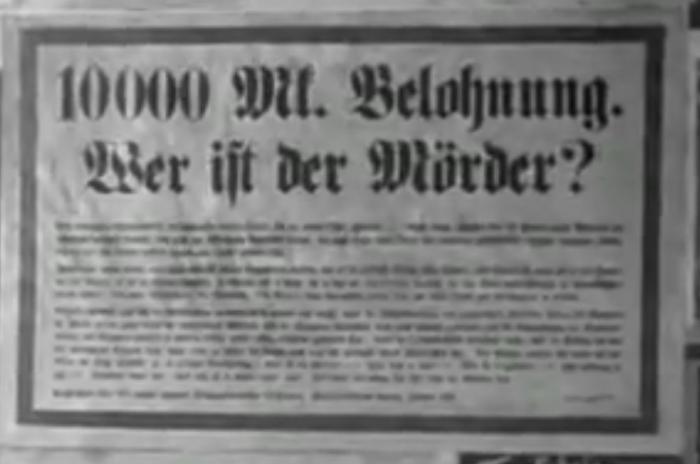
Schrift aus "M- Eine Stadt sucht einen Mörder"
Suche die Schriftart von dem Plakat aus M - Eine Stadt sucht einen Mörder
Ich würde vermuten, dass es eine andere Variante der Schrift ist, die Dieter Steffmann als Schmalfette Fraktur digitalisiert hat. Letztere unterscheidet sich vor allem durch ein moderneres k, ein anderes Fragezeichen und eine andere Laufweite (was aber vermutlich der Digitalisierung geschuldet ist).